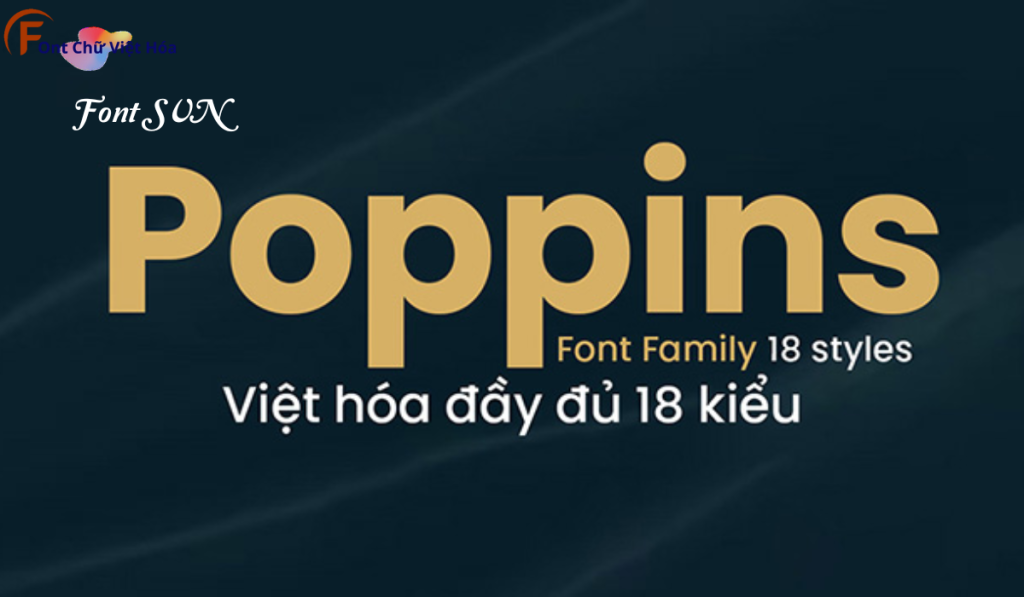
Font SVN Poppins Việt Hóa
Tác giả: SVN Poppins Việt Hóa
Ngôn ngữ: Tiếng Việt, Latin, Cyrillic
Bộ Font: SVN
Phân loại: Hiện đại, Cá tính, Thanh lịch, Linh hoạt
Độ dày: Mỏng, Vừa, Đậm, Đậm Vừa, Đen
Font SVN Poppins Việt Hóa là một font chữ không chân hiện đại, thuộc bộ font SVN. Được thiết kế với mục tiêu mang lại sự tinh tế và thanh lịch, font này phù hợp cho các dự án thiết kế như website, tài liệu, và bao bì sản phẩm. Với các nét chữ rõ ràng và độ dày đều đặn, Font SVN Poppins Việt Hóa không chỉ dễ đọc mà còn tạo cảm giác chuyên nghiệp. Việc Việt hóa font giúp người dùng dễ dàng sử dụng trong các thiết kế tiếng Việt, mang lại sự tiện lợi và thẩm mỹ cao.